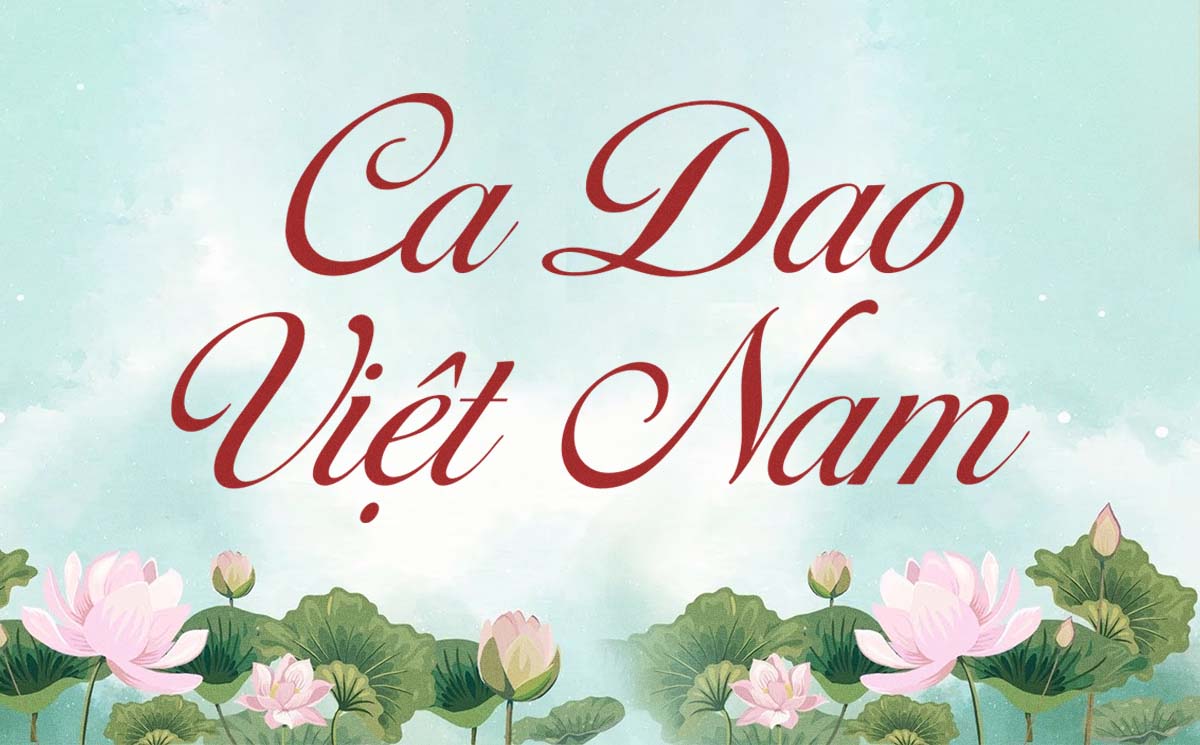
Trong nghệ thuật thiết kế thiệp cưới, font chữ đóng vai trò vô cùng quan trọng giúp truyền tải cảm xúc chân thành và thông điệp tình yêu tinh tế của cặp đôi đến các vị khách mời. Font chữ viết tay, chữ ký mềm mại cho thiệp cưới, đám cưới SVN Balladeer Light ra đời như một giải pháp hoàn hảo, mang lại vẻ đẹp thanh lịch, bay bổng và vô cùng sang trọng cho từng ấn phẩm cưới. Với bộ nét uốn lượn tự nhiên cùng các ký tự Việt hóa hoàn chỉnh, đây chắc chắn là công cụ không thể thiếu của các designer chuyên nghiệp trong mùa cưới năm nay.
Font Chữ Viết Tay, Chữ Ký Mềm Mại Cho Thiệp Cưới, Đám Cưới SVN Balladeer Light – Điểm Nhấn Nghệ Thuật Cho Tấm Thiệp Sang Trọng
Mỗi tấm thiệp cưới không chỉ đơn thuần là một lời mời, mà còn là câu chuyện tình yêu được khắc họa qua ngôn ngữ hình ảnh và con chữ. Thiết kế thiệp cưới hiện đại ngày nay đòi hỏi sự kết hợp hài hòa giữa yếu tố truyền thống và hơi thở lãng mạn của nghệ thuật hiện đại. Việc lựa chọn một typeface phù hợp có thể nâng tầm toàn bộ bố cục, tạo nên sự khác biệt ngay từ cái nhìn đầu tiên.
SVN Balladeer Light là phiên bản Việt hóa đặc sắc của dòng font script viết tay kiểu chữ ký (signature style). Với trọng lượng chữ nhẹ nhàng (Light), font mang đến cảm giác thanh thoát, tinh khôi nhưng vẫn giữ được nét quyến rũ đầy đẳng cấp. Sự mềm mại trong từng đường nét của SVN Balladeer Light giúp thể hiện trọn vẹn sự ngọt ngào, tinh tế mà các cặp đôi muốn gửi gắm trong ngày trọng đại của cuộc đời.
Các Tính Năng Và Ưu Điểm Nổi Bật Của Font SVN Balladeer Light
1. Đường Nét Viết Tay Tự Nhiên Và Nét Chữ Ký Bay Bổng Sang Trọng
SVN Balladeer Light sở hữu thiết kế dựa trên nét chữ ký thủ công tinh tế. Các đường nét nối tiếp nhau một cách tự nhiên, có độ thanh độ đậm hài hòa như được viết ra từ ngọn bút lông hay ngọn bút máy cao cấp. Nét chữ nét mảnh (Light weight) tạo cảm giác không gian thoáng đãng, giúp bố cục thiệp cưới trở nên thanh thoát hơn bao giờ hết. Sự kết hợp giữa các đường cong uốn lượn uyển chuyển và sự tự do của phong cách calligraphic giúp bộ font chữ đám cưới này thoát khỏi sự cứng nhắc của các font chữ truyền thống.
2. Bộ Ký Tự Việt Hóa Hoàn Chỉnh, Tối Ưu Cho Ngôn Ngữ Tiếng Việt
Một trong những nỗi lo lớn nhất của các nhà thiết kế Việt Nam khi sử dụng các font chữ script quốc tế là lỗi dính dấu, mất nét hoặc các dấu thanh (sắc, huyền, hỏi, ngã, nặng) bị thô cứng, lệch tông so với tổng thể nét chữ. SVN Balladeer Light đã được việt hóa tỉ mỉ từng chi tiết, điều chỉnh khoảng cách và hình dáng của từng dấu thanh sao cho ăn khớp hoàn hảo với các chữ cái. Điều này đảm bảo rằng tên cô dâu, chú rể hay các dòng thông điệp bằng tiếng Việt vẫn giữ nguyên tính thẩm mỹ cao nhất mà không gặp bất kỳ lỗi hiển thị nào.
3. Tích Hợp Hệ Thống Glyphs, Swashes Và Alternates Đa Dạng
Để tạo ra những mẫu thiệp cưới độc bản, SVN Balladeer Light cung cấp một kho tàng các ký tự thay thế (Stylistic Alternates) và đường nét trang trí uốn lượn (Swashes/Ligatures). Người dùng có thể dễ dàng tùy biến điểm đầu, điểm cuối của các từ ngữ hoặc tạo ra những nét biến tấu chữ ký vô cùng ấn tượng. Nhờ tính năng này, bạn có thể tự tay tạo ra những logo tên cặp đôi (monogram) độc đáo, cá nhân hóa từng chi tiết nhỏ nhất trên thiệp mời, menu tiệc cưới hay bảng chào đón khách (welcome board).
5. Ứng Dụng Đa Dạng Ngoài Lĩnh Vực Thiết Kế Thiệp Cưới
Dù được sinh ra như một lựa chọn hoàn hảo cho thiệp cưới và sự kiện lãng mạn, SVN Balladeer Light còn thể hiện sự linh hoạt đáng kinh ngạc trong nhiều lĩnh vực sáng tạo khác. Bạn hoàn toàn có thể ứng dụng font chữ ký mềm mại này cho:
- Thiết kế nhận diện thương hiệu: Logo thời trang, mỹ phẩm, spa, studio chụp ảnh cưới, tiệm hoa tươi.
- Ấn phẩm truyền thông: Banner quảng cáo, nhãn mác sản phẩm handmade, bao bì quà tặng cao cấp.
- Nghệ thuật chữ (Typography): Trích dẫn tình yêu (quotes), bìa sách, thiệp mừng sinh nhật, thiệp Giáng sinh.
- Chữ ký số và Watermark: Đóng dấu bản quyền ảnh chụp cho các nhiếp ảnh gia chuyên nghiệp.
Tại Sao Nên Chọn SVN Balladeer Light Cho Dự Án Thiết Kế Đám Cưới Của Bạn?
Trong thiết kế đồ họa cưới, tính cảm xúc và nét nữ tính, ngọt ngào luôn được ưu tiên hàng đầu. SVN Balladeer Light đáp ứng trọn vẹn nhu cầu này nhờ khả năng gợi mở cảm xúc chân thật. Nét chữ không quá cầu kỳ gây rối mắt, nhưng đủ sự mềm mại để thu hút ánh nhìn.
Bên cạnh đó, việc phối hợp SVN Balladeer Light với các font chữ Serif sang trọng (như Cormorant Garamond, Bodoni) hoặc font Sans-serif hiện đại (như Montserrat, Helvetica) sẽ tạo nên một tổng thể bố cục vô cùng ăn ý. Bạn có thể dùng SVN Balladeer Light cho các phần tiêu đề chính như “Thiệp Mời”, “Tên Cô Dâu & Chú Rể”, và dùng font chữ không chân cho các thông tin chi tiết như ngày giờ, địa điểm để đảm bảo tính dễ đọc.